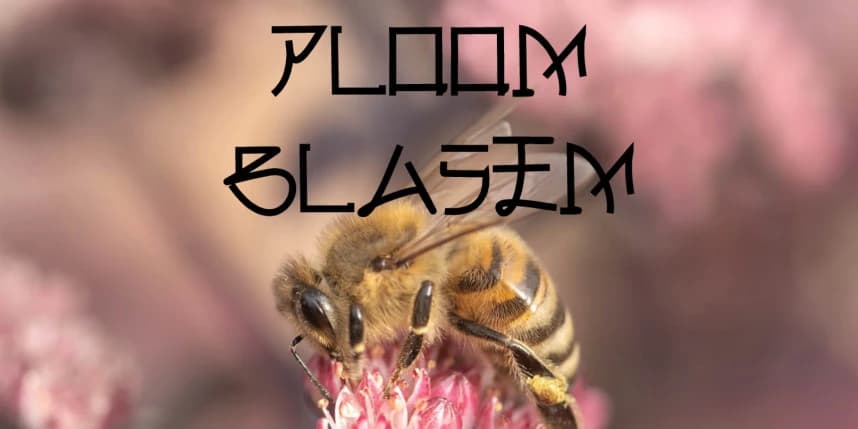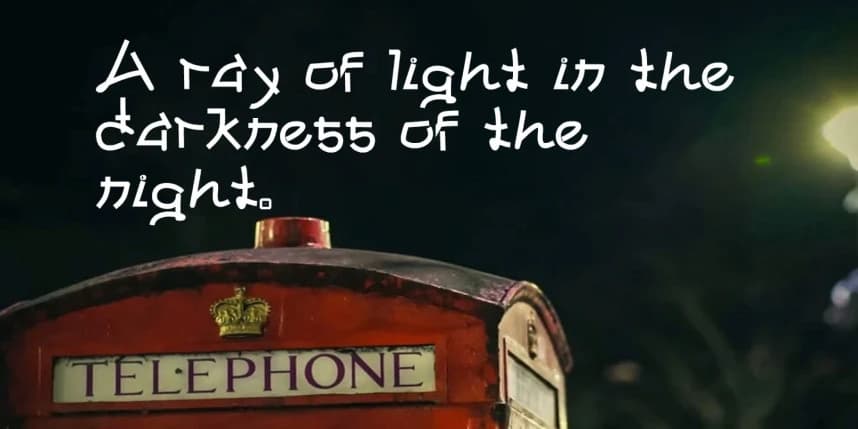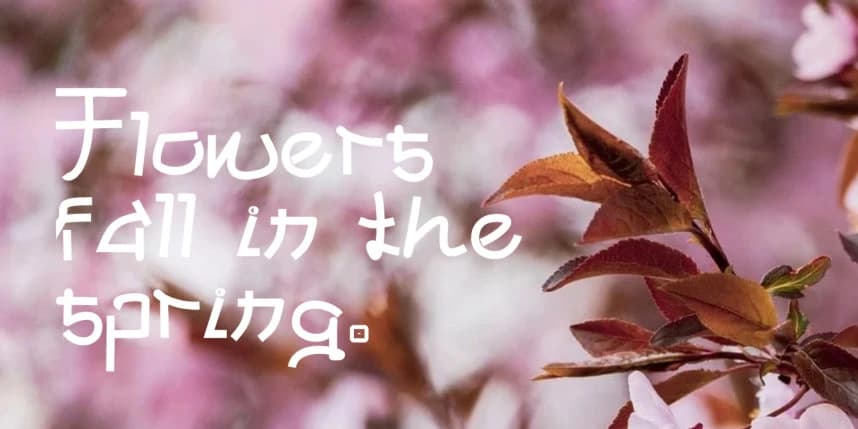
Ploom Font
Ploom Font, modern zerafeti atmosferik bir çekicilikle harmanlayan büyüleyici bir gösterim yazı tipidir. Cesur, akıcı hatları ve benzersiz eğrileri doğal biçimlerin güzelliğini çağrıştırır ve troposfer ile stratosfer arasındaki sınırda görülen rüzgarlar ile bulutları anımsatır.
Ploom Font, modern zarafeti atmosferik bir çekicilikle buluşturan etkileyici bir gösterim yazı tipidir. Kalın, akıcı hatları ve benzersiz eğrileri, doğal biçimlerin güzelliğini çağrıştırır; troposfer ile stratosfer arasındaki sınırda bulunan rüzgârlar ve bulutları hatırlatır.